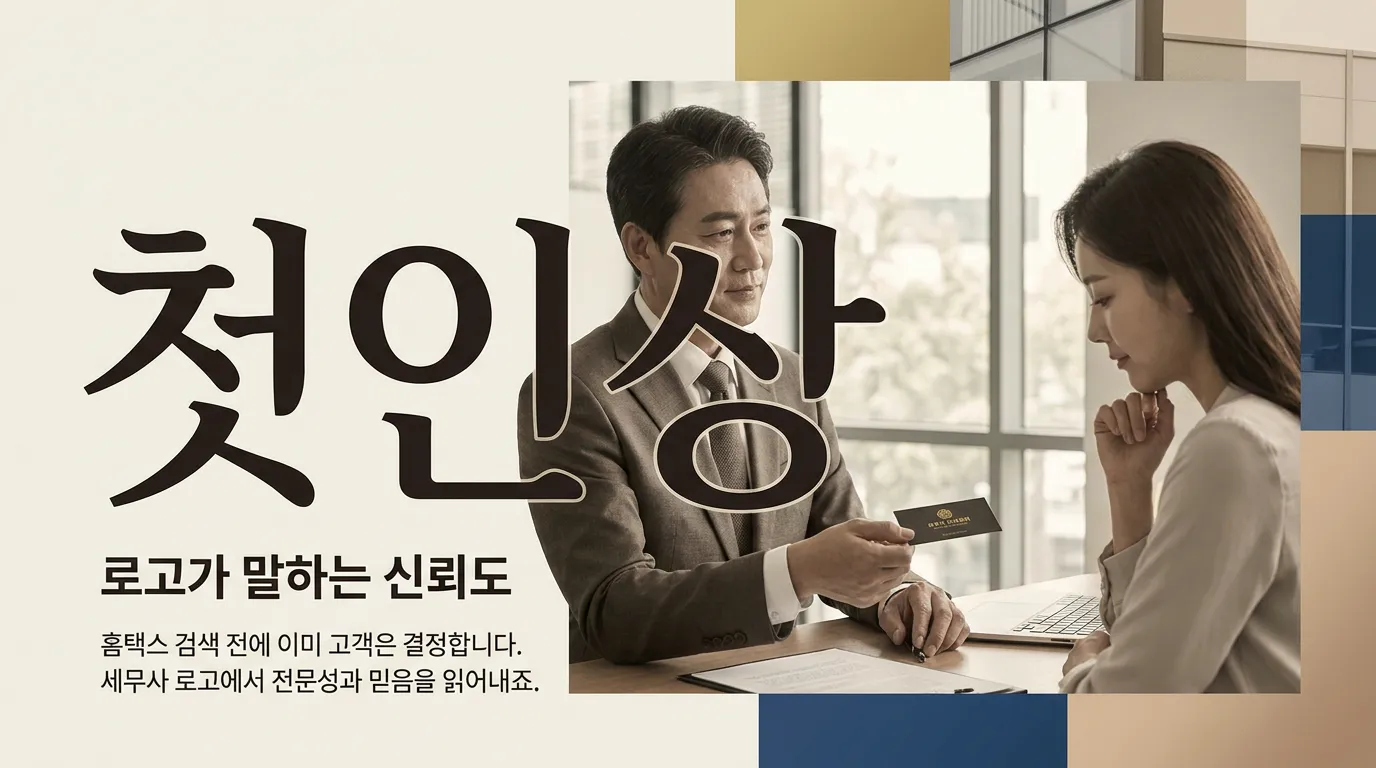
세무사 로고 디자인, 첫 상담 전에 믿음이 생기는 색·폰트 조합 5가지
세무사 사무소 로고가 가벼워 보이지 않게 만드는 컬러와 폰트 조합을 실무 기준으로 정리했습니다.
홈택스 검색창에 사무소 이름을 치기 전, 고객은 이미 로고에서 ‘맡겨도 되나’를 한 번 판단합니다.
왜 세무사 로고는 예쁜 것보다 ‘덜 가벼운 것’이 먼저일까요?
대표님들이 가장 많이 놓치는 지점이 있습니다. 세무사 로고 디자인을 카페 로고처럼 만들면 안 된다는 점입니다. 부드럽고 귀여운 로고가 나쁘다는 뜻은 아닙니다. 다만 세금 문제를 들고 온 고객은 ‘친근함’보다 ‘내 자료를 실수 없이 다룰 사람인가’를 먼저 봅니다.
한국세무사회 자료에는 1만7천 세무사공동체라는 표현이 나옵니다. 또 2025년 5월 31일 기준 개업 회원 수가 16,095명이라는 보도도 있었습니다. 선택지가 많다는 뜻이에요. 이름만으로 구분되기 어렵다면, 첫 화면의 색과 글자가 사무소의 태도를 대신 말해야 합니다. (down.kacpta.or.kr)
3초 안에 안정적으로 보이는 색은 무엇일까요?
저라면 세무사 사무소에는 원색 파랑, 쨍한 초록, 번쩍이는 금색을 먼저 빼겠습니다. 화면에서는 튀지만, 세무 자료를 맡기는 장면에서는 가벼워 보일 수 있습니다. 대신 채도를 낮춘 색을 씁니다.
추천 조합은 5가지입니다. ①딥 네이비+아이보리, 정갈한 고딕. 가장 안전합니다. ②차콜+블루그레이, 숫자를 많이 다루는 법인 세무에 좋습니다. ③딥 그린+웜그레이, 상속·증여처럼 긴 상담이 필요한 분야에 맞습니다. ④먹색+오프화이트, 경력과 무게를 보여주기 좋습니다. ⑤다크 브라운+뮤트 골드, 고액 자산가 대상일 때만 절제해서 씁니다.
핵심은 ‘고급색’이 아니라 ‘낮은 채도’입니다. 세무는 확신을 파는 업이 아니라 오류를 줄이는 업에 가깝습니다. 색도 그 태도를 따라가야 합니다.
폰트는 세리프가 좋을까요, 고딕이 좋을까요?
한 가지 폰트로 끝내면 대개 평범해집니다. 사무소명은 단단한 고딕, 보조 문구는 얇은 명조나 세미세리프로 잡아보세요. 예를 들면 ‘정우세무회계’는 굵은 고딕으로, ‘Tax Advisory Office’나 ‘상속·법인 전문’은 얇게 빼는 식입니다.
KCI에 실린 도시 브랜드 아이덴티티 관련 자료에서도 로고타입, 심벌, 컬러, 서체가 시각 정체성을 이루는 항목으로 반복 언급됩니다. 저는 여기서 서체를 특히 봅니다. 같은 네이비라도 둥근 폰트면 보험 영업처럼 보이고, 획이 너무 얇으면 책임감이 약해 보입니다. (journal.kci.go.kr)
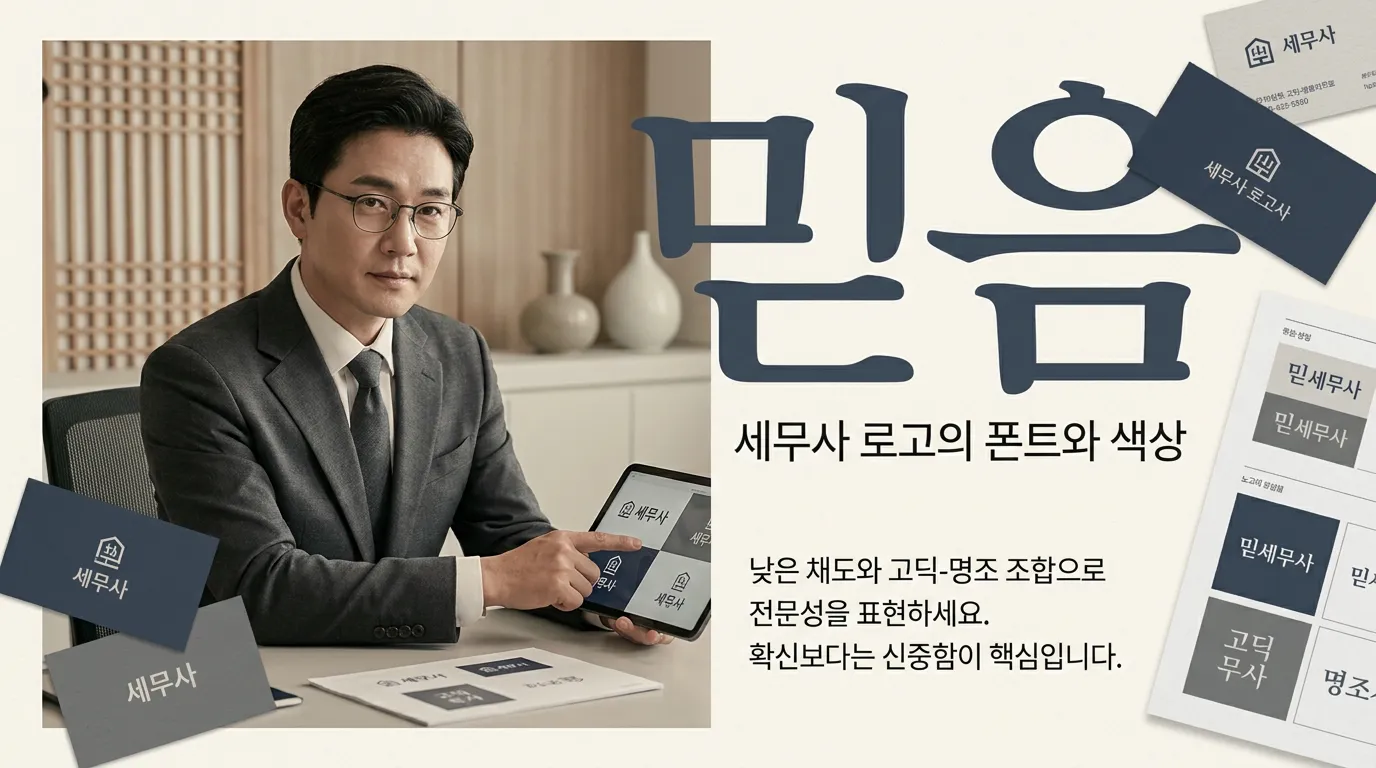
로고가 작아졌을 때도 읽히나요?
세무사 로고는 간판보다 명함, 카카오톡 프로필, 견적서 PDF, 신고 안내문에서 더 자주 보입니다. 그래서 멀리서 멋진 로고보다 작게 줄였을 때 안 깨지는 로고가 이깁니다.
웹 접근성 기준으로 자주 쓰이는 WCAG는 일반 텍스트와 배경의 대비를 4.5:1 이상으로 봅니다. 로고도 똑같이 생각하면 됩니다. 흰 바탕에 연회색 글자, 금색 얇은 획, 베이지 배경 위 브라운 소문자는 고급스러워 보여도 모바일에서는 흐립니다. (w3.org)
심볼은 세금 계산기 모양이면 충분할까요?
계산기, 도장, 원형 테두리, 저울. 세무사 로고에서 너무 많이 보이는 소재입니다. 문제는 고객이 기억할 이유가 없다는 겁니다. 심볼을 넣고 싶다면 업종 설명보다 사무소의 방식에서 출발하세요. 빠른 신고 대리인지, 법인 자문인지, 상속 전문인지에 따라 선의 굵기와 구조가 달라져야 합니다.
지금 쓰는 로고를 휴대폰 화면에서 2cm 크기로 줄여보고, 사무소명·업종·분위기가 동시에 읽히는지 확인해보세요. 작품 둘러보기 전에 이 한 번의 테스트가 방향을 정해줍니다.